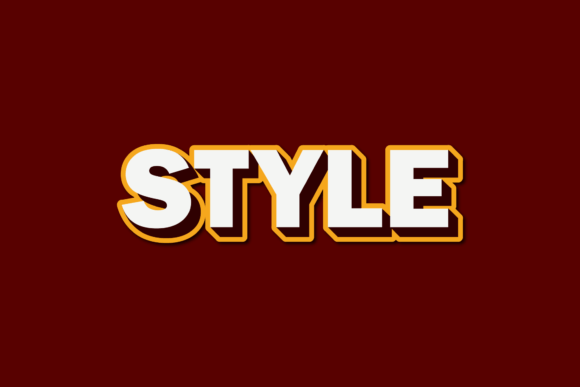
Typhography Style Graphic Design Art
Ulasan Detalhada: Typhography Style Graphic Design Art
Se você está em busca de um recurso de design que combine tipografia criativa e versatilidade de formato, o pacote Typhography Style Graphic Design Art é a escolha perfeita. Neste review, destacamos os pontos fortes, os benefícios práticos e porque esse produto deve estar no seu arsenal de criação.
Por que este design se destaca?
1. Qualidade visual impecável
A arte tipográfica foi criada com atenção meticulosa ao espaçamento, contraste e hierarquia visual, garantindo impacto imediato em qualquer aplicação.
2. Totalmente editável
- Versatilidade – Ideal para branding, posts de mídia social, banners, mockups de produtos e até projetos de corte a laser.
O Typhography Style Graphic Design Art entrega exatamente o que promete: design tipográfico de alta qualidade, pronto para ser editado e usado em múltiplas plataformas. Seja você um designer freelancer, uma agência ou um empreendedor que deseja reforçar a identidade visual, este pacote oferece valor excepcional a um preço acessível.